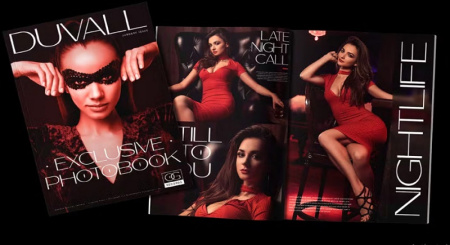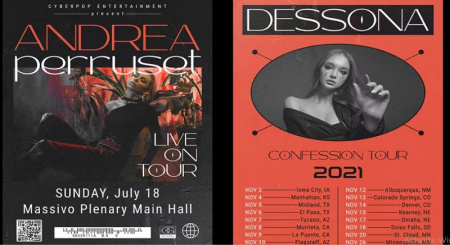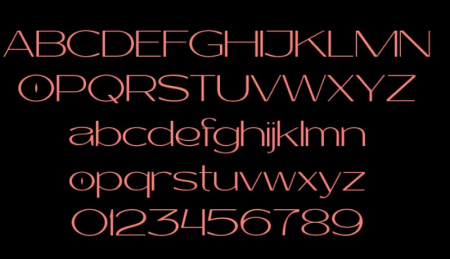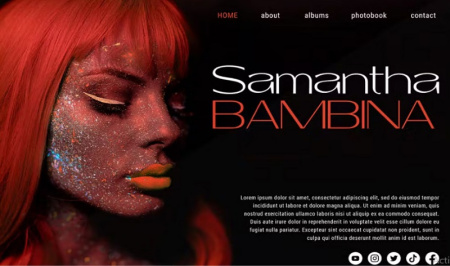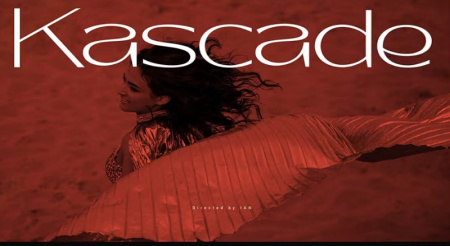
دانلود فونت انگلیسی Pomp Adore
دانلود فونت انگلیسی Pomp Adore برای جلد آلبوم هنری ، وب سایت، شرکت در رویدادهای موسیقی، نماهنگ، لباس و کالا، مجله، کتاب عکس می باشد. شما می توانید در طراحی های مختلف از این فونت انگلیسی زیبا استفاده نمایید. فونت Pomp Adore برای اهداف شخصی یا تجاری شما.
دانلود فونت انگلیسی مدرن Pomp Adore
✅ نام فونت: Pomp Adore